Bạn đang tìm kiếm một phông chữ hiện đại, dễ đọc cho website hay thiết kế của mình? Font chữ không chân (hay Sans Serif) chính là câu trả lời. Với các nét chữ tối giản, không có chi tiết “chân” thừa, loại font này đảm bảo văn bản hiển thị rõ ràng và sắc nét trên mọi màn hình kỹ thuật số.
Đây không phải là một lựa chọn ngẫu nhiên. Hầu hết các giao diện website và ứng dụng di động hiện đại đều ưu tiên sử dụng chúng để tối ưu trải nghiệm người dùng. Việc hiểu rõ sự khác biệt giữa loại font này và phông chữ có chân (Serif) là bước đầu tiên để tạo ra một thiết kế chuyên nghiệp, thay vì chỉ lựa chọn theo cảm tính.
Trong bài viết này, chúng tôi sẽ giải thích cặn kẽ tại sao loại font này lại chiếm ưu thế trong thiết kế hiện đại. Bạn sẽ khám phá các ưu điểm vượt trội, cách phân biệt và kết hợp chúng một cách hài hòa, cũng như nhận được danh sách các font chữ không chân đẹp và miễn phí được chuyên gia tin dùng.
Hãy bắt đầu bằng việc tìm hiểu định nghĩa và các đặc điểm cốt lõi đã làm nên sức mạnh của chúng.
Font chữ không chân là gì và tại sao lại quan trọng?
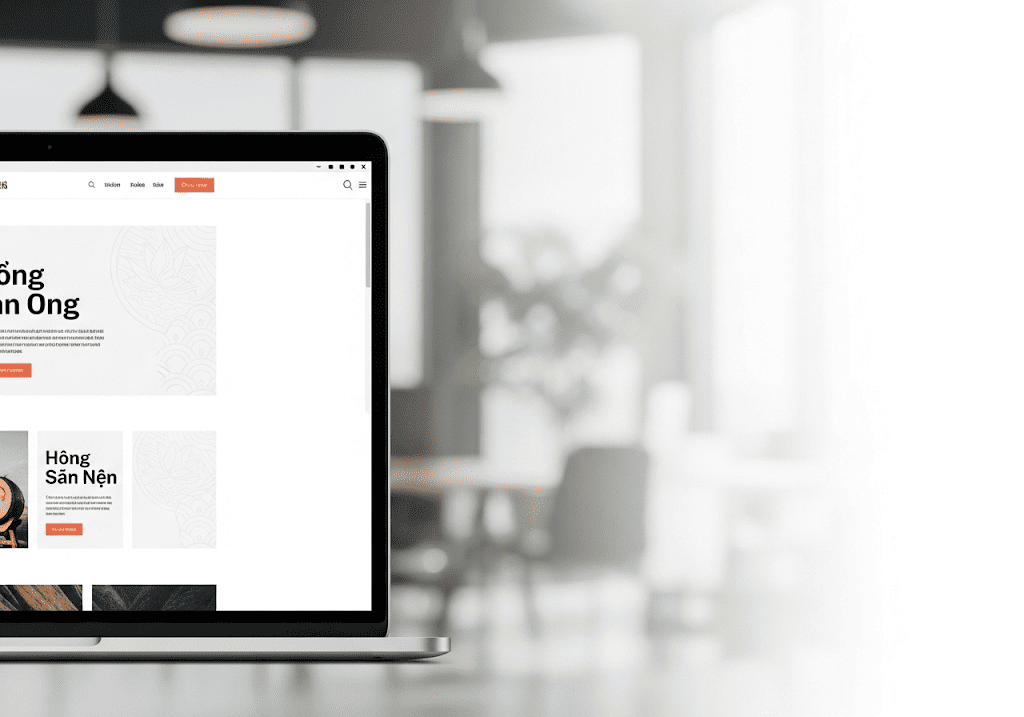
Bắt đầu với font chữ không chân: Đặc điểm và vai trò trong thiết kế hiện đại?
Font chữ không chân, hay còn gọi là sans-serif (bắt nguồn từ tiếng Pháp, “sans” nghĩa là “không có”), là loại phông chữ có các nét chữ được thiết kế tối giản, không có các chi tiết “chân” nhỏ ở cuối mỗi ký tự. Đặc điểm này giúp font mang lại cảm giác hiện đại, rõ ràng và dễ đọc, đặc biệt trên các màn hình kỹ thuật số có độ phân giải khác nhau, từ màn hình máy tính đến điện thoại di động.
Để nhận biết, bạn chỉ cần thực hiện một phép so sánh đơn giản: hãy đối chiếu font Arial (không chân) với Times New Roman (có chân). Nhìn vào chữ “T” hoặc “i”, bạn sẽ thấy Arial có các đầu nét thẳng và gọn, trong khi Times New Roman có các gạch ngang nhỏ ở chân và đỉnh. Sự tối giản này không chỉ là về thẩm mỹ; nó là một lựa chọn có chủ đích trong thiết kế hiện đại, giúp truyền tải thông điệp một cách trực tiếp, không rườm rà và tối ưu hóa trải nghiệm người dùng trên giao diện số.
Hiểu rõ sự khác biệt này là bước nền tảng trong nghệ thuật typography chuyên nghiệp. Việc lựa chọn phông chữ phù hợp không chỉ ảnh hưởng đến tính dễ đọc mà còn định hình cá tính thương hiệu. Để đa dạng hóa phong cách và tìm hiểu thêm về các loại font độc đáo, bạn có thể tham khảo thêm về font chữ thư pháp việt hóa. Đây cũng là lý do tại sao việc tìm hiểu sâu hơn về các ưu điểm vượt trội của loại font này, như chúng ta sẽ khám phá ở phần tiếp theo, lại quan trọng đến vậy để xây dựng một website hiệu quả.
Ưu điểm vượt trội của font chữ không chân trong thiết kế website?
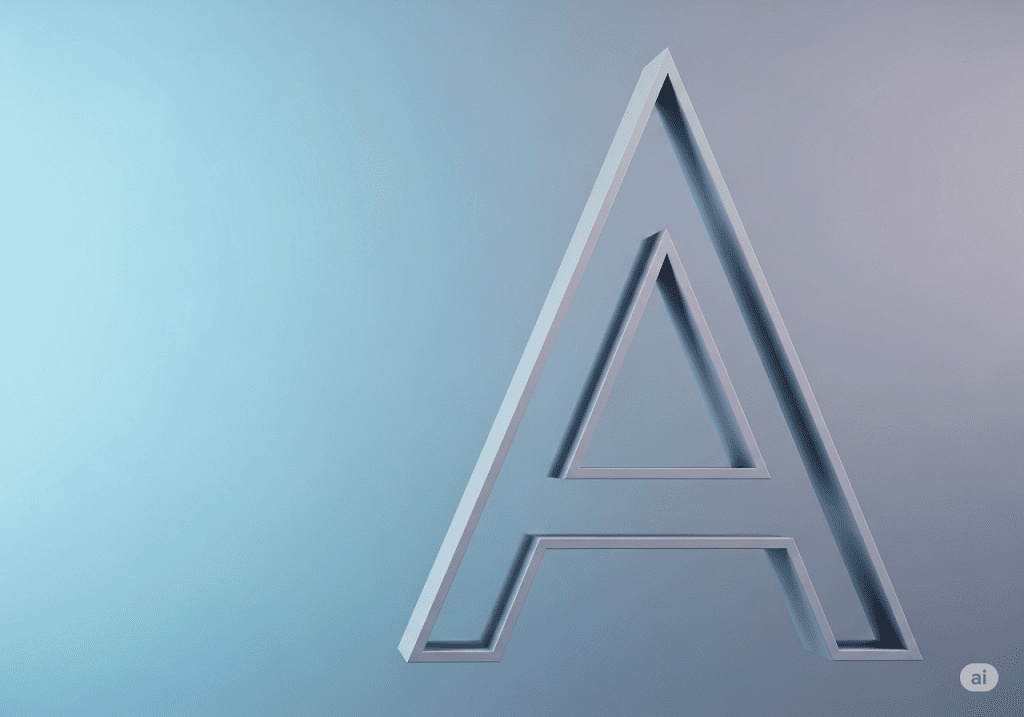
Tại sao font không chân là lựa chọn tối ưu cho website của bạn?
Các ưu điểm font không chân nổi bật nhất nằm ở tính dễ đọc vượt trội trên màn hình kỹ thuật số và sự linh hoạt trong ứng dụng. Do không có các chi tiết “chân” rườm rà ở cuối nét chữ, loại font này hiển thị rõ ràng và sắc nét ngay cả ở kích thước nhỏ hoặc trên các màn hình có độ phân giải thấp, giúp người dùng không bị mỏi mắt khi đọc nội dung dài.
Sự đơn giản này chính là sức mạnh của chúng. Ví dụ, tại Tini Tech, khi thiết kế website WordPress cho khách hàng, chúng tôi thường ưu tiên các font như Roboto hoặc Open Sans cho phần thân bài. Lý do là chúng đảm bảo trải nghiệm đọc mượt mà trên mọi thiết bị, từ desktop đến mobile, một yếu tố cốt lõi của UI/UX hiện đại. Việc lựa chọn đúng font cho website không chỉ là về thẩm mỹ, mà còn là một quyết định chiến lược ảnh hưởng trực tiếp đến trải nghiệm người dùng.
Các lợi ích chính bao gồm:
- Tính rõ ràng: Cấu trúc đơn giản giúp các ký tự không bị dính vào nhau, tối ưu khả năng đọc nhanh và chính xác trên giao diện số.
- Tính linh hoạt: Dễ dàng kết hợp với các loại font khác và phù hợp cho nhiều mục đích, từ tiêu đề lớn, nút bấm (CTA) cho đến các đoạn văn bản dài.
- Cảm giác hiện đại: Font không chân thường gắn liền với sự tối giản, công nghệ và thân thiện, giúp định vị thương hiệu của bạn một cách hiệu quả trong mắt người dùng.
Việc hiểu rõ những lợi thế này là bước đầu tiên để lựa chọn phông chữ một cách có chủ đích, thay vì chỉ dựa vào cảm tính.
Phân biệt font chữ không chân và có chân (Serif vs. Sans-serif)
Làm thế nào để phân biệt và lựa chọn giữa font có chân và không chân?
Để phân biệt font có chân và không chân, hãy nhìn vào các chi tiết nhỏ ở cuối nét chữ. Font có chân (Serif) có các “chân” này, tạo cảm giác cổ điển, trang trọng. Ngược lại, font không chân (Sans-serif) có các nét chữ thẳng, gọn gàng, mang lại cảm giác hiện đại và rõ ràng, đặc biệt hiệu quả cho văn bản trên màn hình kỹ thuật số.
Sự lựa chọn giữa hai loại font này ảnh hưởng trực tiếp đến thông điệp và cá tính thương hiệu của bạn. Tại Tini Tech, chúng tôi xem việc tư vấn typography là một phần quan trọng trong quá trình sáng tạo, giúp khách hàng quyết định giữa phong cách đáng tin cậy, truyền thống hay hiện đại, đổi mới.
Để giúp bạn ra quyết định nhanh hơn, đây là bảng so sánh trực quan:
Nên sử dụng bao nhiêu font chữ trên một website là hợp lý?
Một quy tắc vàng trong thiết kế là không nên dùng quá 2-3 font chữ khác nhau trên một website. Việc giới hạn số lượng font giúp đảm bảo tính nhất quán cho thương hiệu và quan trọng hơn là không làm chậm tốc độ tải trang. Mỗi font chữ là một yêu cầu HTTP riêng, sử dụng quá nhiều sẽ ảnh hưởng tiêu cực đến hiệu suất trang, một yếu tố quan trọng cho cả SEO và trải nghiệm người dùng.